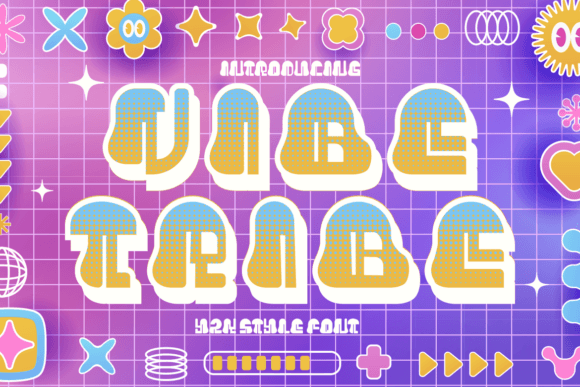
Vibe Tribe
適切なデザイン要素を見つけるのは難しい場合がありますが、Vibe Tribeは作品を即座に引き立てる優れたコレクションを提供します。
POD(オンデマンド印刷)製品、結婚式の招待状、またはソーシャルメディアのグラフィックを作成している場合でも、Vibe Tribeは理想的です。